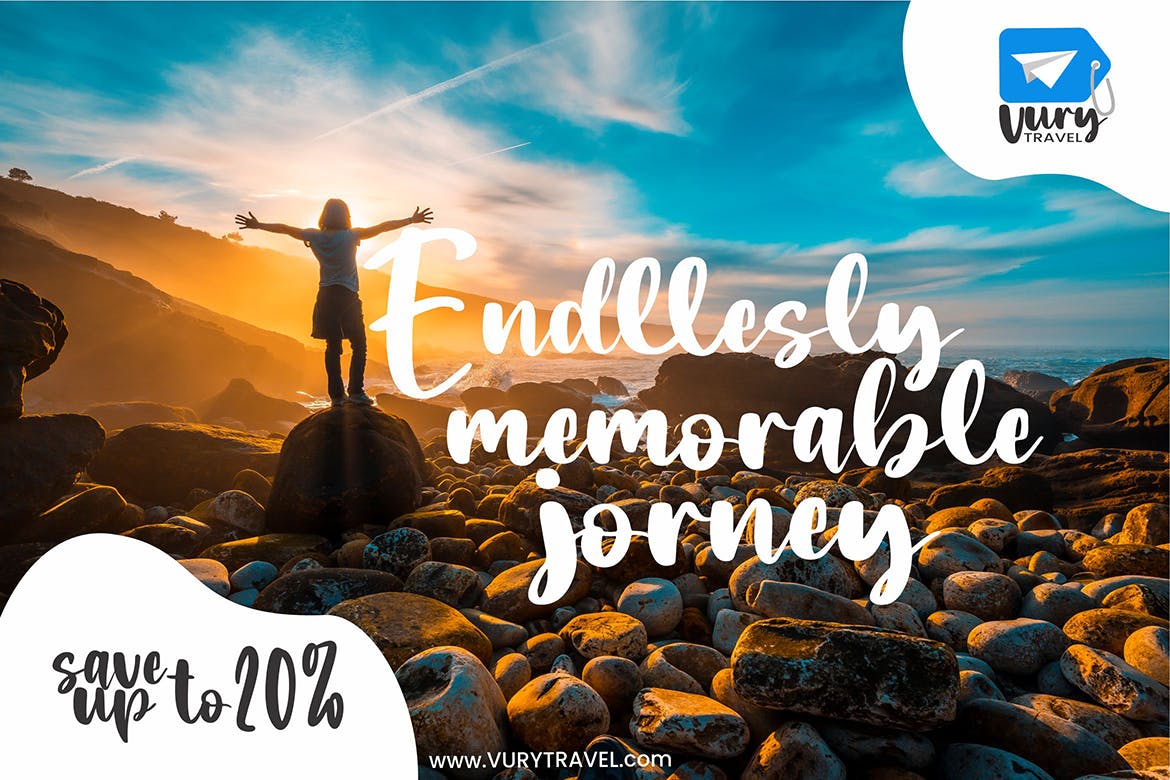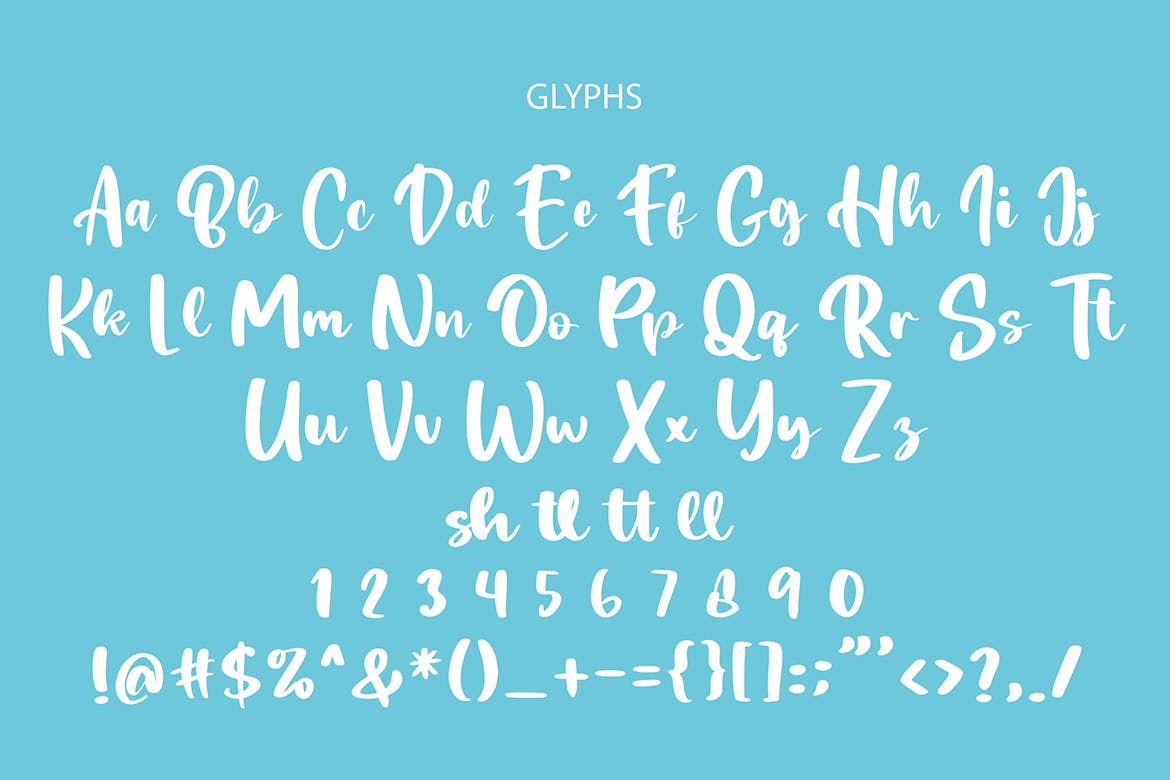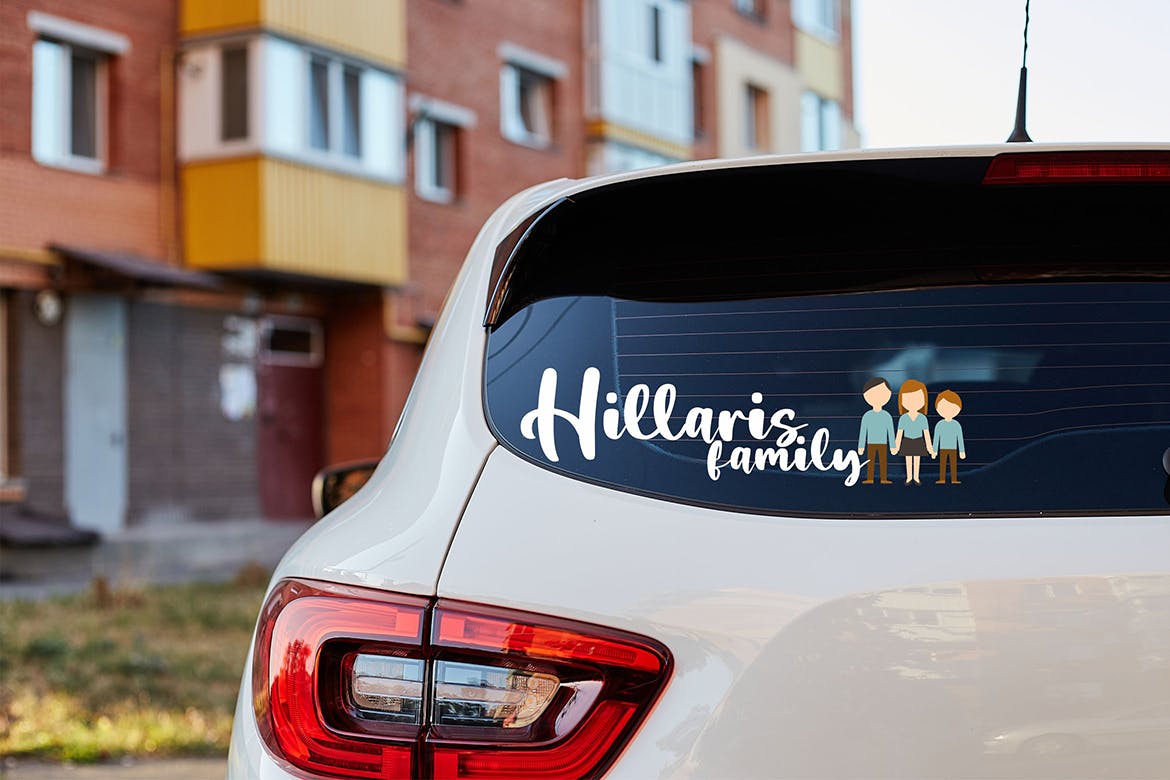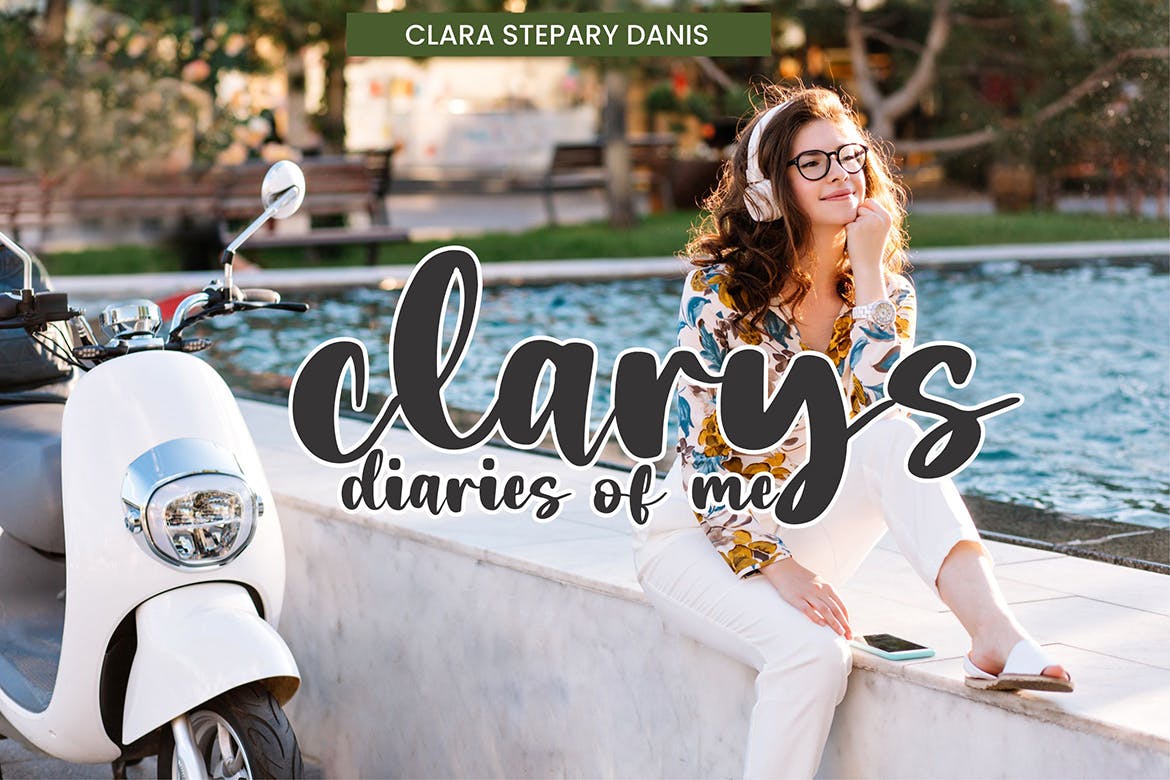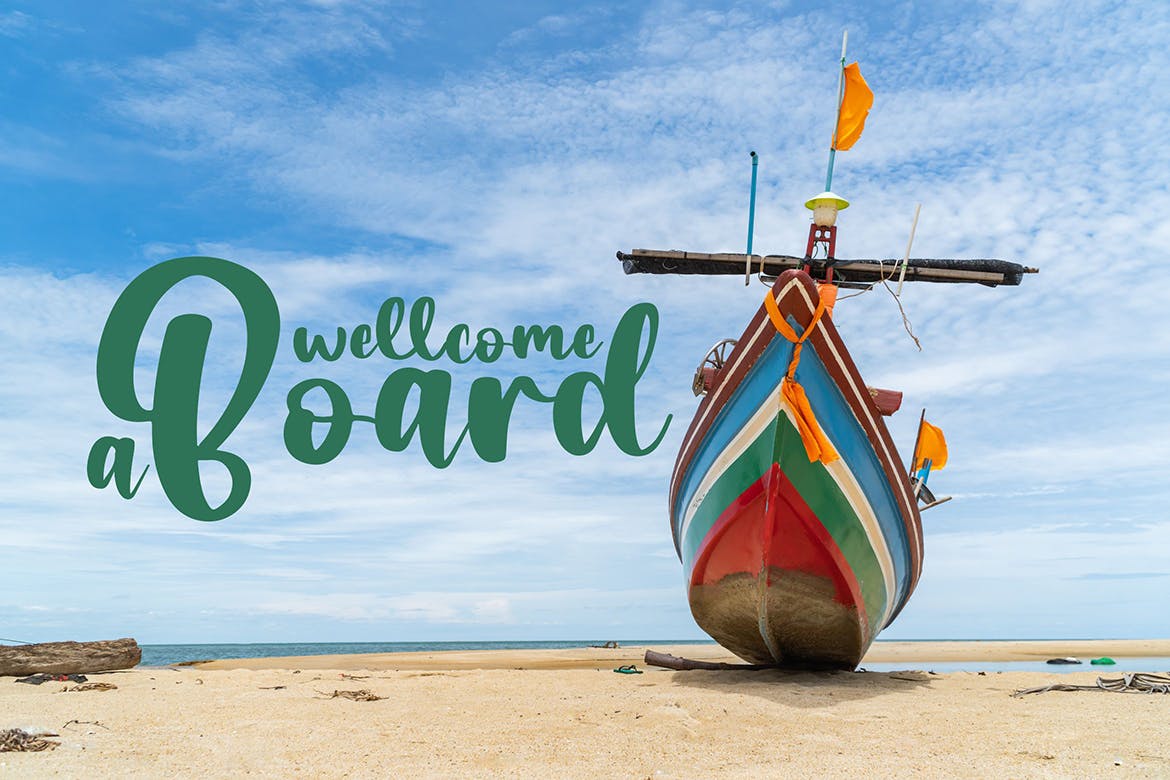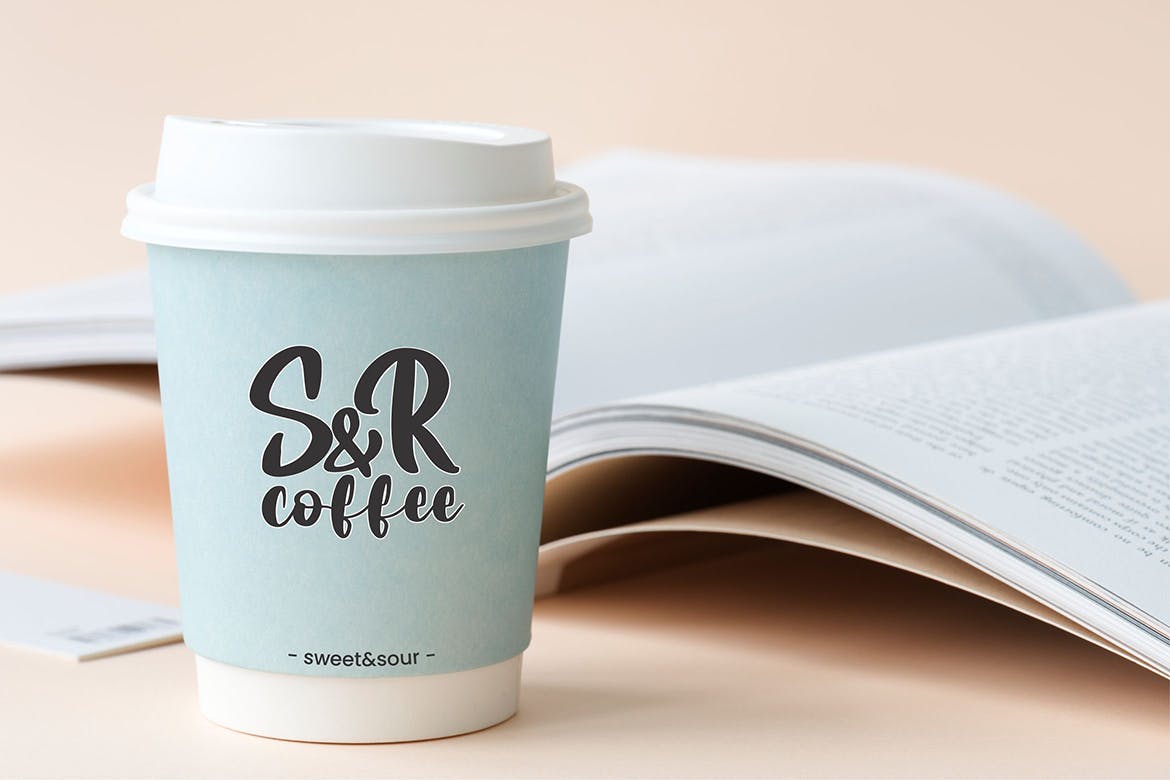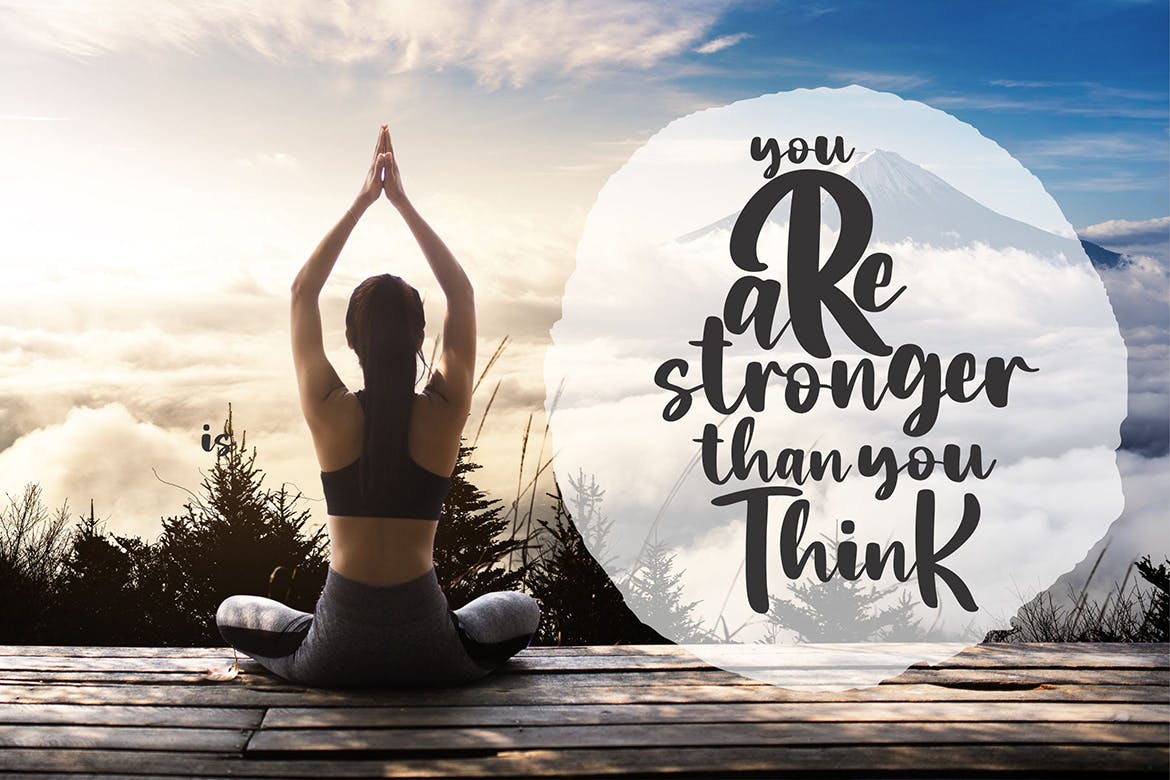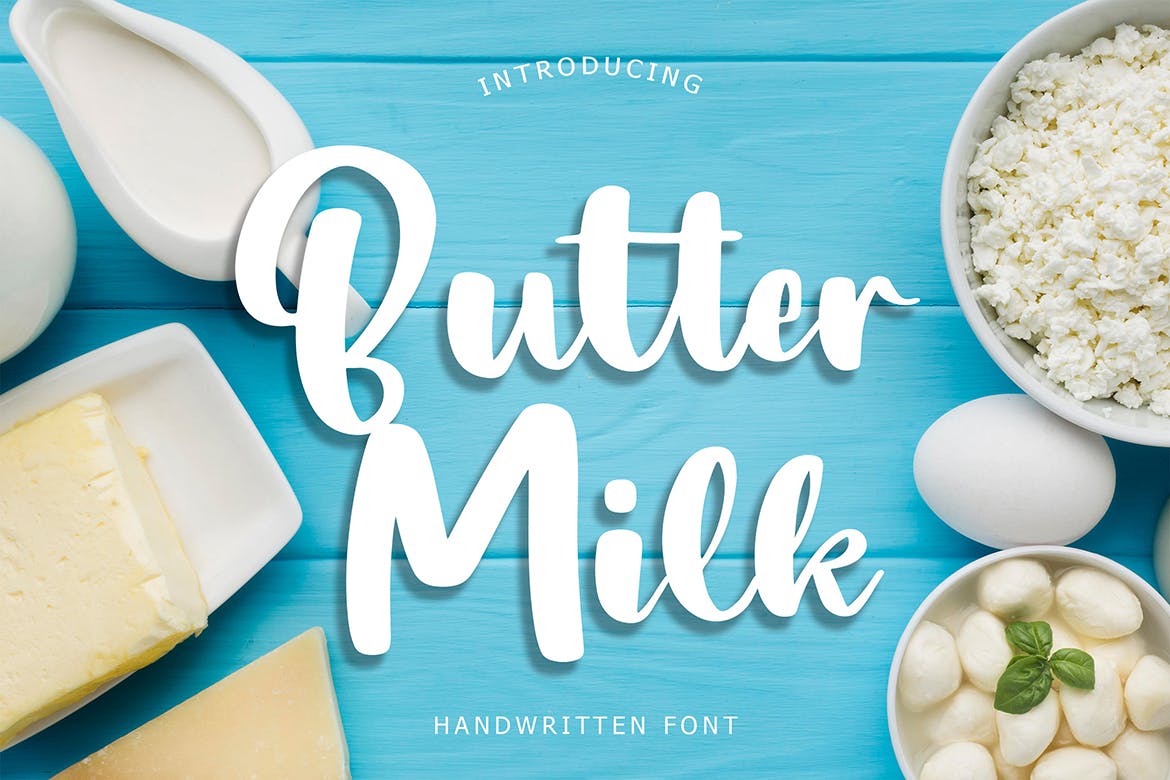
Buttermilk یک فونت دستنویس مدرن است که میتواند متن شما را به شیوهای نوین و جذاب نمایش دهد!
این فونت برای پروژههای برندینگ، طراحی لوگو، طراحی دعوتنامههای عروسی، پستهای شبکههای اجتماعی، تبلیغات، بستهبندی محصولات، طراحی تیشرت، طراحی محصولات، برچسبها، عکاسی، واترمارک، دعوتنامهها، لوازمالتحریر و هر نوع پروژه دیگری مناسب است.